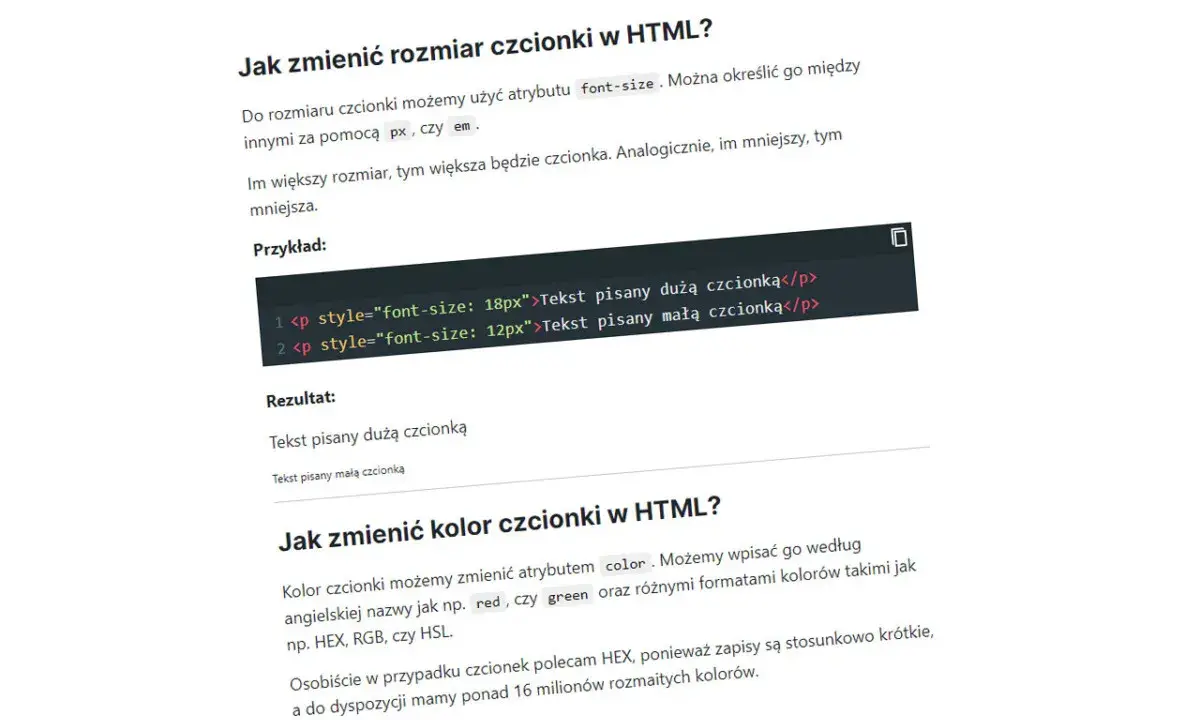
Rozmiar czcionki w rzeczywistości - Jak to działa?
Przykład zmiany rozmiaru czcionki w HTML: 18px dla dużej, 12px dla małej. Pokazuje to, jak rozmiar czcionki w rzeczywistości wpływa na tekst.
W praktyce o wyglądzie tekstu decydują nie tylko cyfry widoczne w programie, ale też metryka kroju, papier i sposób druku. To właśnie rozmiar czcionki w rzeczywistości bywa najbardziej mylący, bo 12 pt nie oznacza automatycznie takiej samej wysokości liter w każdym fontcie. Poniżej rozkładam ten temat na proste zasady: jak czytać punkty typograficzne, jak przeliczać je na milimetry i jak dobrać wielkość pisma do konkretnego wydruku.
Najważniejsze liczby i zasady, które warto zapamiętać
• 1 punkt typograficzny to w praktyce około 0,353 mm.
• Rozmiar w punktach odnosi się do pola pisma, a nie do wysokości samej litery.
• Dwa kroje o tym samym stopniu mogą wyglądać zupełnie inaczej, bo różnią się wysokością małych i wielkich liter.
• Przed drukiem warto oglądać plik w skali 100%, bez automatycznego dopasowania do strony.
• W tekstach ciągłych najczęściej sprawdzają się zakresy 10-12 pt, ale ostateczny efekt zależy od kroju, papieru i odległości czytania.
Co naprawdę mierzy punkt typograficzny
Punkt typograficzny to jednostka umowna, którą od dawna opisuje się wielkość pisma. W standardzie używanym w większości programów DTP przyjmuje się, że 1 pt = 1/72 cala, czyli około 0,353 mm. To wygodny przelicznik, ale nie należy go mylić z fizyczną wysokością liter, bo stopień pisma obejmuje cały projekt znaku, a nie tylko widoczną kreskę na papierze.
W praktyce oznacza to jedną ważną rzecz: liczba w polu „rozmiar” mówi o skali kroju, a nie o tym, ile milimetrów zajmuje najwyższa litera. Dlatego 10 pt w jednym foncie może wyglądać spokojnie i lekko, a w innym wydawać się niemal zbyt drobne do czytania. Z mojego punktu widzenia to podstawowy błąd początkujących: traktują punkt jak linijkę, a on działa bardziej jak wspólny język opisu niż dosłowna miara krawędzi znaku.
Jeśli to rozdzielisz w głowie, łatwiej zrozumiesz, dlaczego sam numer nie wystarcza do oceny jakości składu. A skoro punkt nie opisuje jeszcze wyglądu litery, trzeba sprawdzić, co właściwie zmienia odbiór tego samego stopnia.
Dlaczego dwa kroje o tym samym stopniu wyglądają inaczej
Tu pojawia się najważniejsze praktyczne rozróżnienie. Ten sam rozmiar w punktach nie daje tego samego efektu, bo każdy krój ma inną metrykę, czyli wewnętrzny układ znaków. Jedna czcionka ma wyższą małą literę, inna szersze litery, jeszcze inna mocniej zarysowane wydłużenia górne i dolne. W efekcie dwa teksty ustawione na 12 pt mogą wyglądać jak 11 pt i 13 pt, choć w programie mają identyczną wartość.
• Em box to umowny kwadrat, na którym opiera się rozmiar kroju.
• Cap height opisuje wysokość wielkich liter, więc wpływa na to, jak „wysoki” wydaje się tekst.
• x-height to wysokość małych liter bez wydłużeń, a ona najmocniej wpływa na wrażenie czytelności w akapicie.
• Wydłużenia górne i dolne to elementy liter takie jak w l, b, p czy g, które zmieniają optyczny rytm wiersza.
Dlatego krój szeryfowy o niskiej x-height może wyglądać delikatniej niż nowoczesna groteska o wyższych małych literach, mimo identycznego stopnia. To właśnie dlatego przy zmianie fontu zawsze sprawdzam nie tylko estetykę, ale też optyczny ciężar tekstu. Jeśli tego nie zrobisz, łatwo przeszacować albo zaniżyć realną wielkość pisma na wydruku.
Najprościej mówiąc: punkt mówi, jak duży jest układ znaku, ale nie obiecuje identycznej wysokości „widocznej” liter. I właśnie dlatego warto przejść od teorii do prostego przeliczenia na milimetry.
Jak przeliczać punkty na milimetry i oceniać efekt na papierze
Jeśli chcesz szybko oszacować realny rozmiar, wystarczy pamiętać o przeliczniku: 1 pt to około 0,353 mm. Z tego wynika, że 10 pt daje mniej więcej 3,53 mm, a 12 pt około 4,23 mm w sensie umownego pola pisma. To nadal nie jest wysokość samej litery, ale wystarcza, by rozsądnie planować układ dokumentu, ulotki czy etykiety.
Rozmiar w pt Około w mm Typowe zastosowanie
6 pt 2,12 mm bardzo drobne przypisy, techniczne oznaczenia
8 pt 2,82 mm podpisy, drobne opisy, przypisy pod zdjęciami
10 pt 3,53 mm gęstszy tekst roboczy, formularze, notatki
12 pt 4,23 mm komfortowy tekst ciągły w większości dokumentów
14 pt 4,94 mm nagłówki, materiały do szybkiego skanowania wzrokiem
18 pt 6,35 mm większe tytuły, oznaczenia, proste komunikaty
Te wartości są pomocne, ale trzeba je czytać rozsądnie. Na papierze matowym i przy słabszym druku drobny tekst potrafi zniknąć szybciej niż na ekranie, więc czasem pół punktu robi większą różnicę niż kolejne ozdobne poprawki w projekcie. Jeśli przygotowujesz plik do druku, robię jedną rzecz niemal zawsze: sprawdzam próbny wydruk na docelowym papierze, bo monitor potrafi przekłamać zarówno wielkość, jak i kontrast. Z tego miejsca już bardzo blisko do pytania, jaki stopień sprawdza się w konkretnych zastosowaniach.